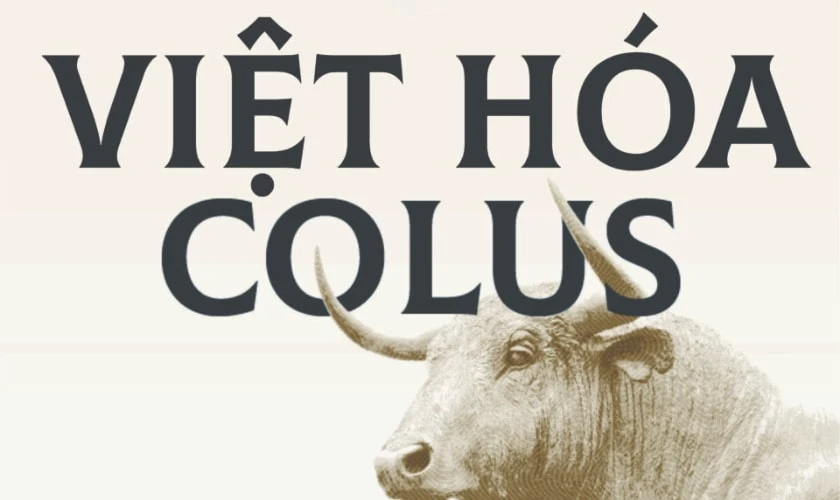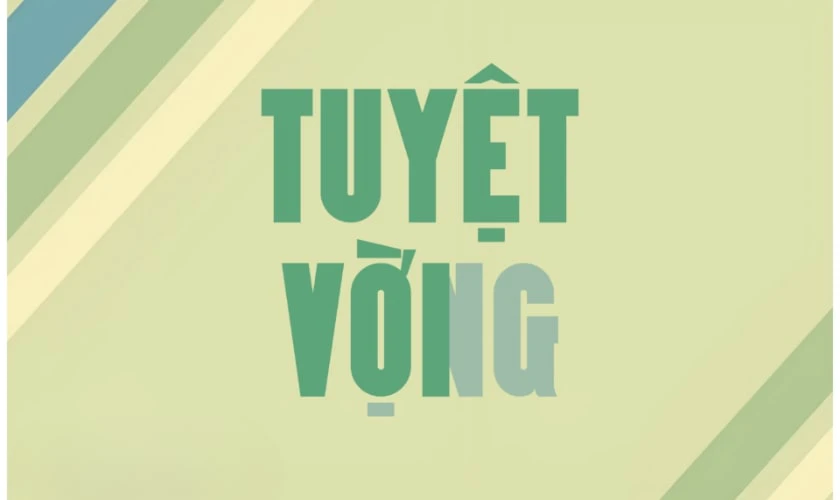
Font chữ 2/9 Việt hóa DFVN Guardilostra được nhiều designer ưa chuộng trong thiết kế poster và banner. Font có kiểu dáng mạnh mẽ, đường nét rõ ràng và dễ đọc. Đây là lựa chọn hoàn hảo cho các dự án in ấn, sự kiện ngày lễ 2/9.
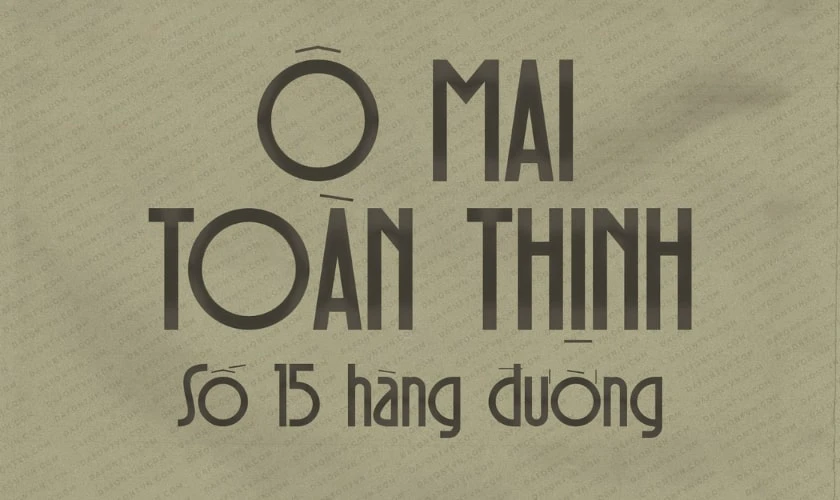
Bộ font hỗ trợ đầy đủ tiếng Việt và đảm bảo tính thẩm mỹ cao. Thế nên, bạn có thể dễ dàng cài đặt và áp dụng trên nhiều phần mềm thiết kế. Font này hứa hẹn mang lại sự chuyên nghiệp và giúp thiết kế nổi bật hơn.
Font chữ 2/9 Independence – Doc lap Typeface mang phong cách hiện đại và tối giản. Kiểu chữ cứng cáp, thanh thoát rất phù hợp cho thiết kế truyền thông ngày Quốc khánh. Font này được nhiều người sử dụng để làm poster, thiệp mời và banner.
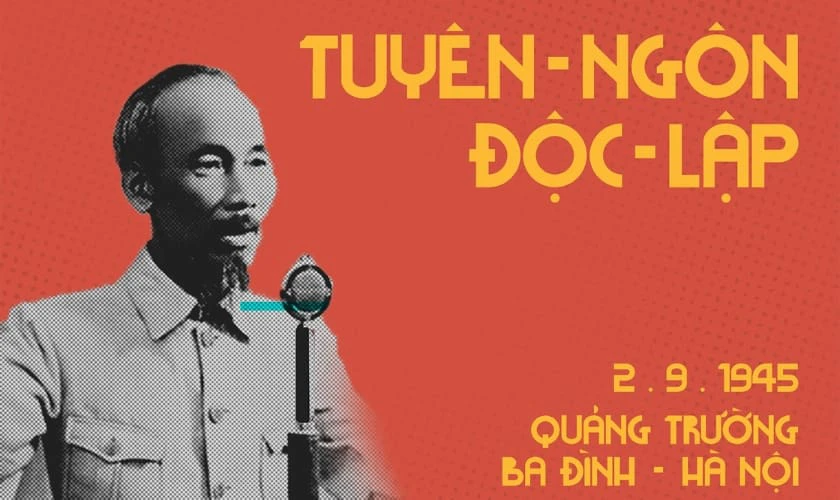
Bộ font có khả năng hiển thị tốt trên cả màn hình và bản in. Nhờ hỗ trợ tiếng Việt đầy đủ, bạn có thể dễ dàng tạo nội dung đẹp mắt. Đây là lựa chọn tuyệt vời cho những ai muốn sự tinh tế.
Font chữ 2/9 Việt hóa UTM Colossalis sở hữu kiểu dáng lớn, mạnh mẽ và thu hút ánh nhìn. Font đặc biệt thích hợp cho các thiết kế tiêu đề, khẩu hiệu và poster sự kiện. Sự cân đối trong từng chi tiết tạo nên sự chuyên nghiệp.
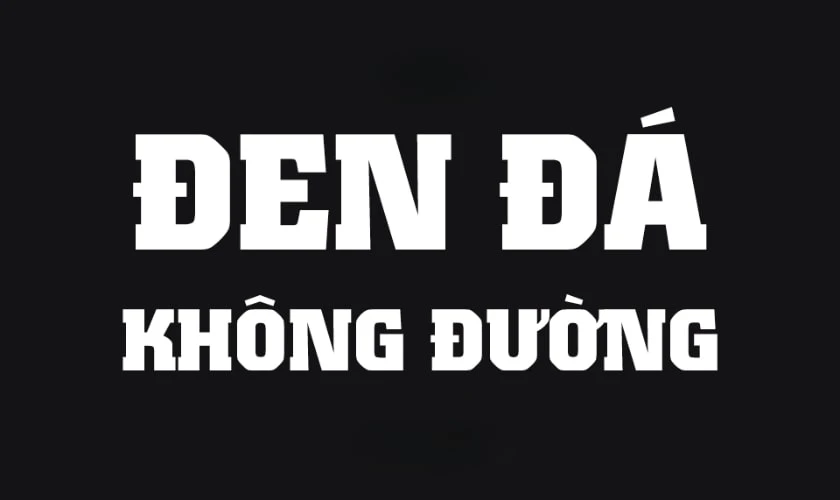
Bộ font hỗ trợ tiếng Việt hoàn chỉnh, dễ đọc và dễ kết hợp cùng nhiều phong cách khác. Bạn có thể áp dụng nhanh chóng trên các phần mềm quen thuộc. Chắc chắn font này sẽ giúp thiết kế nổi bật ngay từ cái nhìn đầu tiên.
Font chữ 2/9 KK7 – Đào, Phở và Piano mang nét sáng tạo. Font phù hợp cho thiết kế mang tính gần gũi và dễ gây ấn tượng. Kiểu chữ độc đáo này giúp poster ngày lễ thêm sinh động.
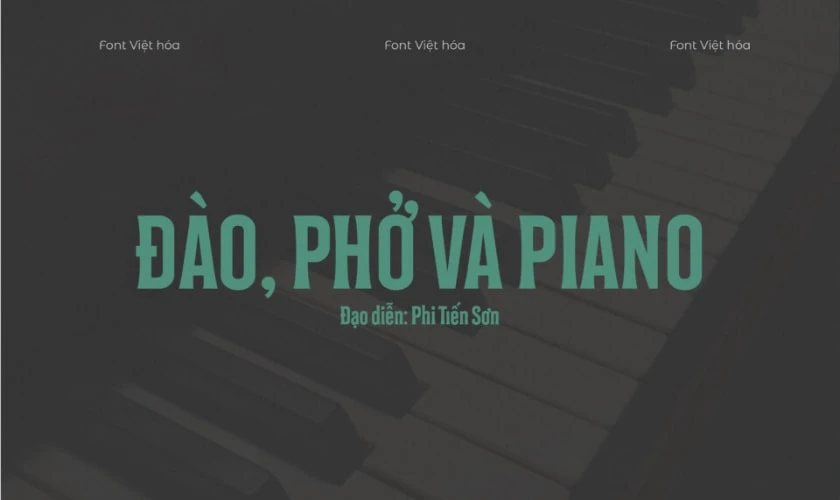
Font hỗ trợ tiếng Việt đầy đủ và dễ dàng sử dụng trong nhiều phần mềm. Bạn có thể kết hợp font với hình ảnh để tăng sức hút. Đây là lựa chọn thú vị cho thiết kế truyền thông 2/9.
Font chữ 2/9 DT Phudu mang phong cách trẻ trung, phóng khoáng và dễ đọc. Font thường được dùng trong thiết kế poster, banner quảng cáo và thiệp chúc mừng ngày lễ. Kiểu dáng mềm mại giúp chữ thêm gần gũi và tự nhiên.
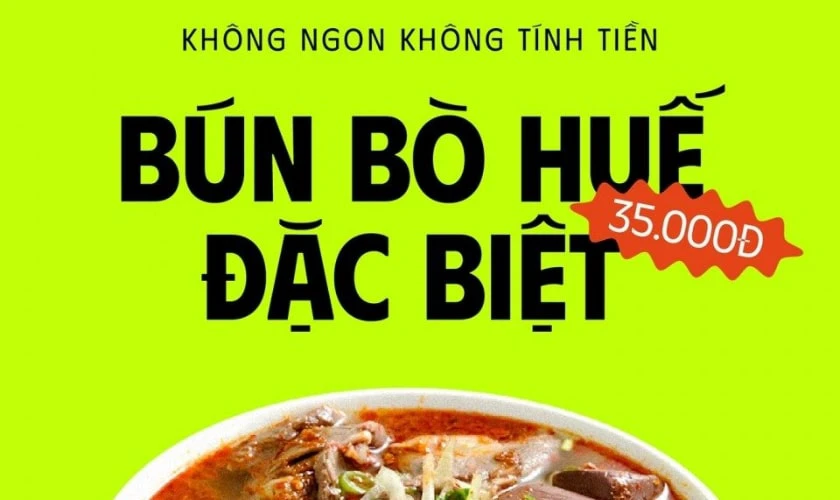
Bộ font này hỗ trợ tiếng Việt tốt và dễ dàng kết hợp với nhiều thiết kế khác nhau. Người mới bắt đầu cũng có thể cài đặt và sử dụng nhanh chóng. Font DT Phudu chắc chắn sẽ giúp nội dung của bạn trở nên nổi bật và thu hút.
Font Huxley-Max-ExtraBlack nổi bật với nét chữ dày và mạnh mẽ. Kiểu chữ này thường được dùng trong tiêu đề, poster và thiết kế sự kiện. Font có khả năng nhấn mạnh nội dung và tạo sự chú ý ngay lập tức.
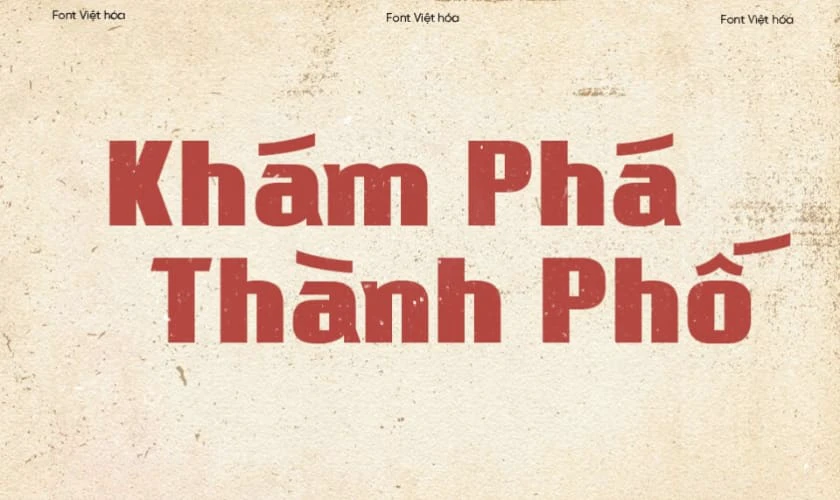
Ngoài ra, Huxley-Max-ExtraBlack dễ kết hợp với nhiều font khác trong cùng dự án. Nhờ tính ứng dụng cao, đây là một trong những font chữ 2/9 được ưa chuộng nhất năm 2025.
Font Neufreit Extra Bold mang phong cách hiện đại và cá tính. Kiểu chữ in đậm giúp văn bản rõ ràng, dễ nhìn và thu hút ánh nhìn. Font này đặc biệt phù hợp trong thiết kế banner, khẩu hiệu và in ấn.
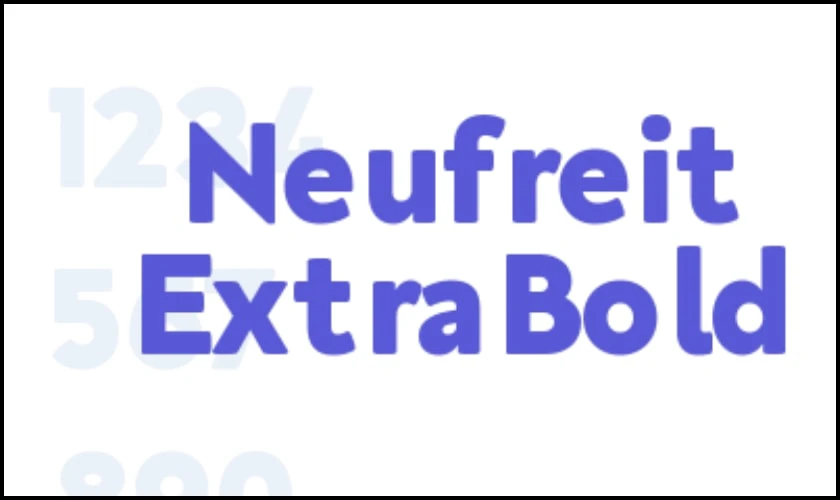
Người dùng lựa chọn Neufreit Extra Bold bởi sự cân đối và linh hoạt. Đây là lựa chọn hoàn hảo nếu bạn muốn tạo điểm nhấn mạnh mẽ cho thiết kế 2/9.
Font chữ 2/9 Rostack mang phong cách cổ điển nhưng không kém phần tinh tế. Font này phù hợp với những thiết kế kỷ niệm, poster truyền thống và ấn phẩm lịch sử. Kiểu chữ tạo cảm giác trang trọng và bền vững.
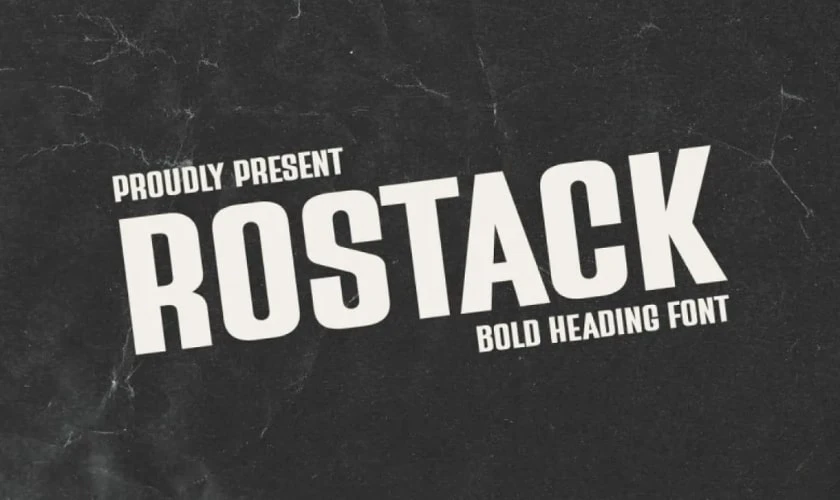
Rostack dễ dùng, thân thiện và có khả năng tương thích nhiều phần mềm. Đây là font chữ 2/9 giúp người thiết kế tiết kiệm thời gian và vẫn giữ được nét đẹp cổ điển.